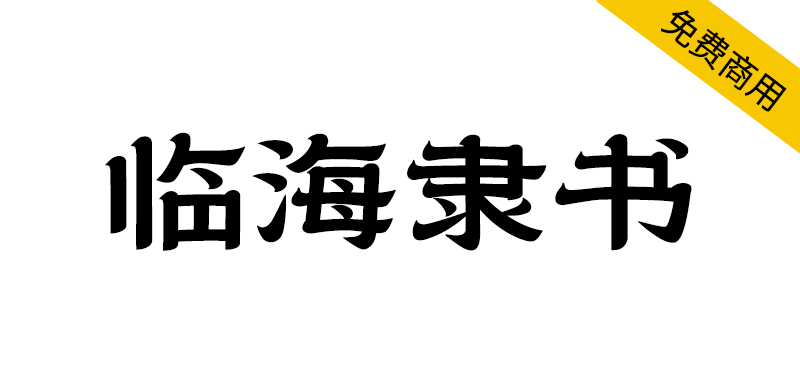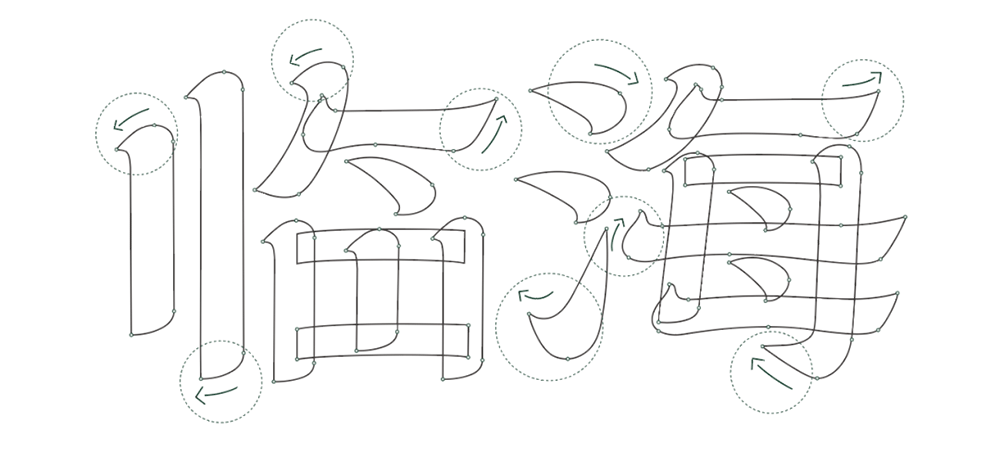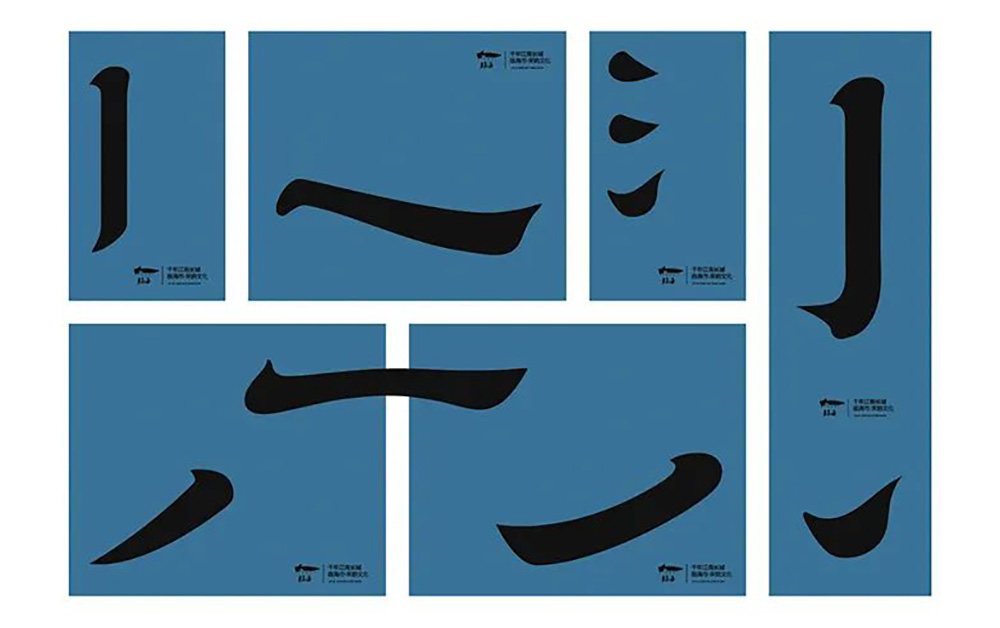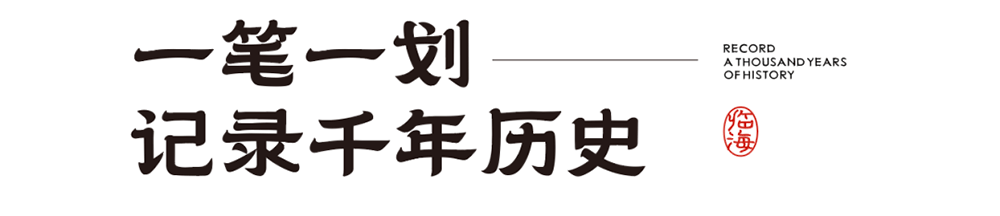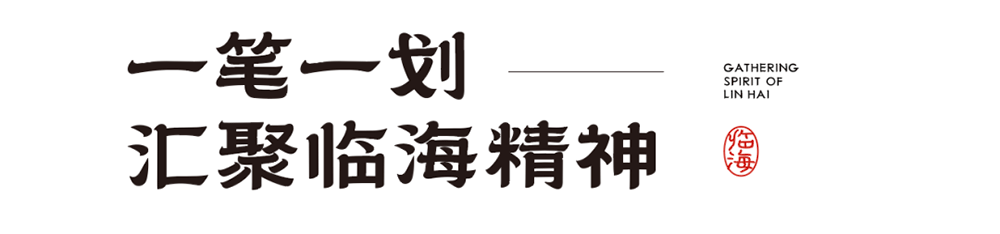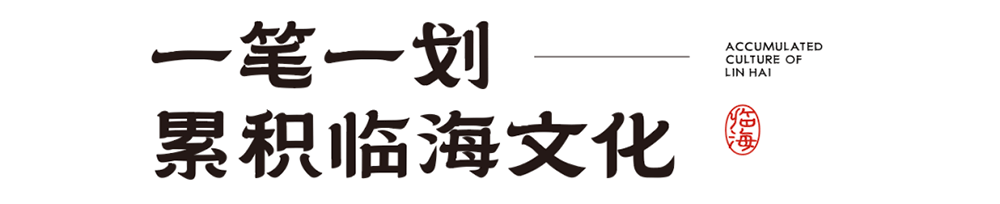
一座城市的影响力取决于城市文化的影响力,经营城市品牌,经营的是一座城市的文化辨识度......,为持续打响“ 千年台州府、江南真宋城 ”文旅品牌形象,让文化传播更具辨识度,市社发集团积极谋划,深度挖掘临海文化内涵,与乡立方团队携手打造推出了拥有临海独特风格和时代烙印的专属字体。
台州府城墙、龙兴寺、千年紫阳街等,文化古迹星罗棋布,骆宾王、戚继光、朱自清等,叙说着临海文化绵长的故事,文人舞墨,匠者筑基,共同铸就了临海的文化底蕴,正因如此临海能较早跻身于“国家历史文化名城”之列,能有信心对世界说“千年古城,最忆临海”。
历史底蕴深厚、文化资源丰富,这是临海不可复制的独特禀赋,但如何让世界认识临海呢,源浚者流长,根深者叶茂,文字是文化传承的标志,临海字体,更是传播临海文化的基础元素。
一城化一字,一字如一城,站在时光的纵轴上向前望去,隶书的演变史,也是临海城市变迁的缩影。
将千年古城、人文繁盛、山水之韵,等临海城市特质,结合汉字五大字体之一的隶书体,隶书,兴盛于汉代,也是临海城市起源的时代,隶书所具有的厚重、古典、拙朴特质,旷达雄浑,古朴内敛,将临海的城市特质展示的淋漓尽致。
临海古城,也就是台州府城,始建于晋,扩建于唐,距今已有1600多年的历史。古城原有七门十三敌台,现仅存四门和四座敌台。
江南长城,是江南地区唯一的长城,城墙依山就势,俯视大江,敌楼林立,气势恢宏,是北方明长城的师范和蓝本,人称“江南八达岭”,现存近5000米,目前已列入世界文化遗产预备名单之中。
紫阳古街,全长1080米,是整个古城的中轴线,有“临海第一古街之称”,街道两边的房屋店铺雕梁画栋、古色古香,保留着宋代遗风、明清格局。
在这里,戚继光驰骋海疆“封侯非我意,但愿海波平”。在这里,骆宾王仗剑而起“宝剑思存楚,金锤许报韩”。“莫言沧海阔,杯度自应知”,最澄大师万里求法,化成千佛塔的“菩萨垂眉,万千悲悯”。
无论是临海词调、黄沙狮子、大石车灯、大田板龙、小芝鼓亭、上盘花鼓、城关细吹亭等传统民间文化艺术,还是糟羹、麦油脂、马蹄酥、羊脚蹄、麦饼、蛋清羊尾等传统风味小吃,亦或是刺绣、草编、竹木雕刻等传统工艺。
府城人民的智慧,凝结于千家万户的烟火之中,汇集成千年临海的独特画卷。
通过临海字体打造临海符号化IP,将临海字体融入到城市的历史、文化、形象、资源、产品、内容等各个层面,让临海字体成为这座城市具有独特辨识度和人格化的城市品牌。
市社发集团×乡立方为临海设计的这款临海隶书字体,可以直接下载和存储在电脑里,你可以在word、ppt里直接打出它,也可以在招牌、包装上使用它,或许还会在电视、手机上随处看见它,它将带着临海的文化和故事传播得更远、更广。